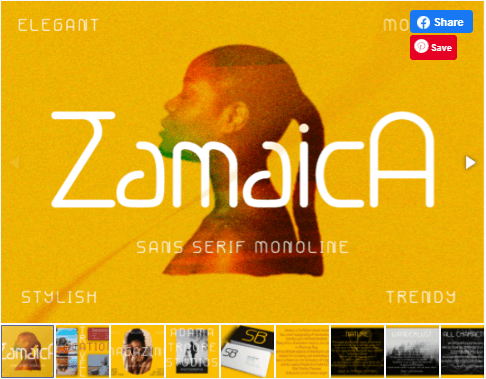
Zamaica Font
Zamaica - это монолиниевый шрифт без засечек с многоязычной поддержкой.
Он идеально подходит для традиционных средств массовой информации и Интернета - отлично подходит для мастеров и художников-графиков, совместим со всеми инструментами. Благодаря своей игривости он отлично подходит для творческих проектов, будь то вдохновляющие настенные плакаты или для рекламы вашего бренда.
Zamaica - это монолиниевый шрифт без засечек с многоязычной поддержкой.
Он идеально подходит для традиционных средств массовой информации и Интернета - отлично подходит для мастеров и художников-графиков, совместим со всеми инструментами. Благодаря своей игривости он отлично подходит для творческих проектов, будь то вдохновляющие настенные плакаты или для рекламы вашего бренда.